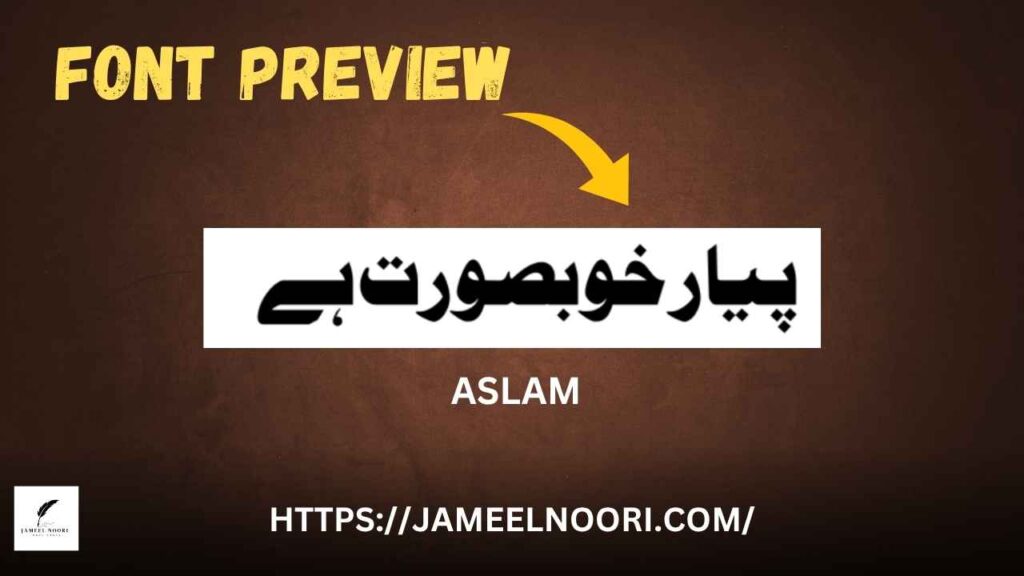
Aslam Aslam urdu Font Kya Hai?
Aslam Aslam Urdu Font download aik TrueType Font (TTF) hai jo Urdu likhne ke liye popular hai. Iska design traditional Naskh style se inspired hai. Yeh font newspaper headlines, official Urdu documents, aur calligraphy design ke liye bohot use hota hai.
Aslam Aslam urdu Font Ki Features
H3: 1. High Clarity
- Saaf aur wazeh Urdu text display karta hai.
H3: 3. Official Document Friendly
- Government aur educational documents ke liye suitable.
Aslam Font Kis Kis Kaam Aata Hai?
H3: 1. Social Media Design
- Urdu quotes ya shayari likhne ke liye best.
H3: 2. Wedding Cards
- Traditional calligraphy touch ke liye Aslam font use hota hai.
H3: 3. Educational Notes
- Urdu assignments aur PDFs mein istimal hota hai.
H3: 4. Blogging aur Websites
- Urdu blogging aur heading fonts ke liye use hota hai.
Aslam font ka best use kya hai?
Urdu headings, social media designs, aur PDF writing mein.
Kya yeh Nastaleeq jaisa lagta hai?
Nahi, yeh Naskh style mein hai jo Nastaleeq se mukhtalif hai.
Kya is font mein harakatein hain?
Is font mein basic harakatein mojood hain.